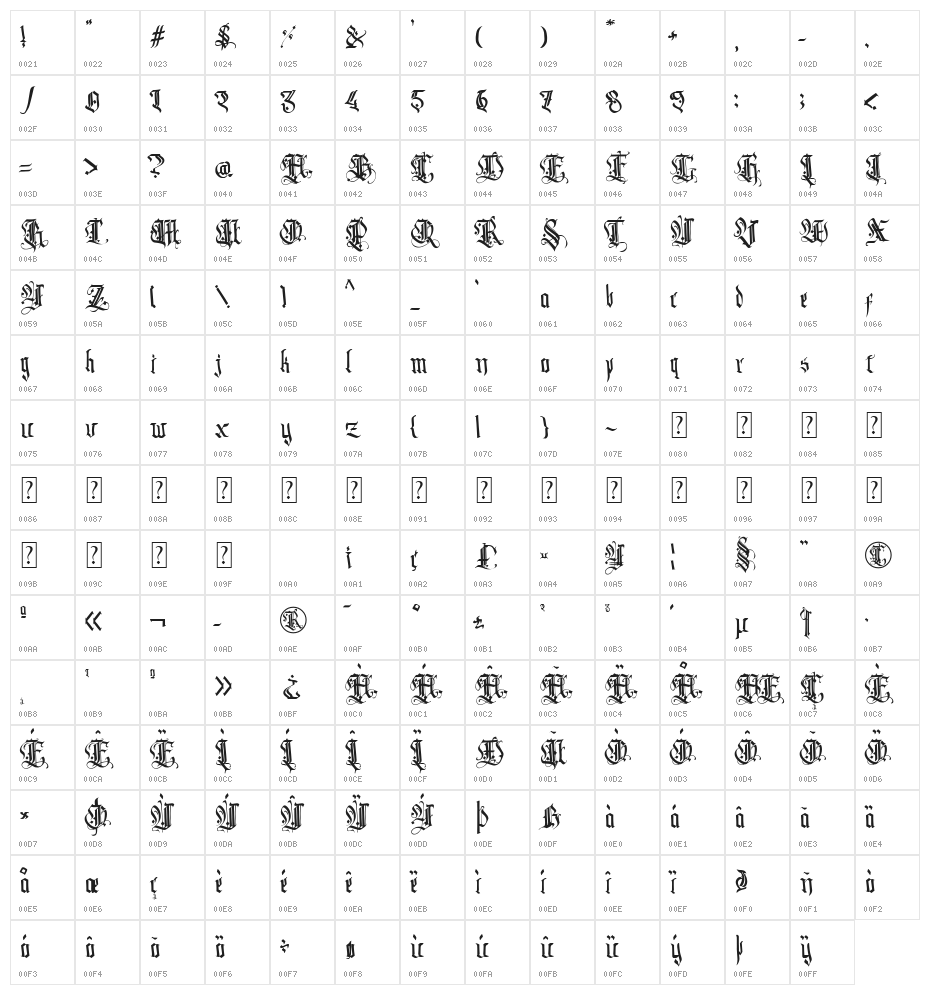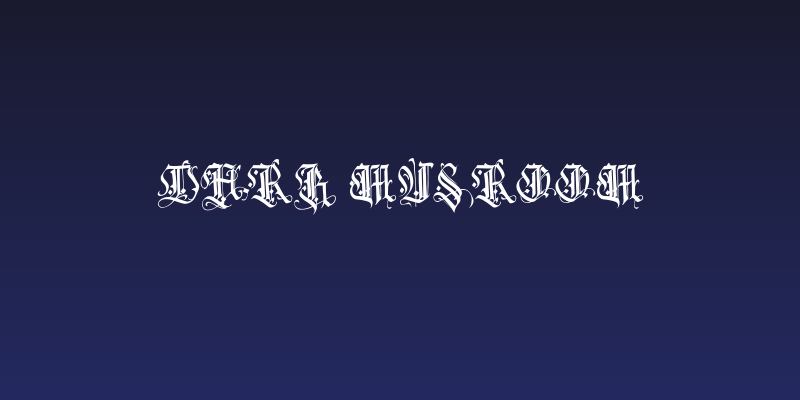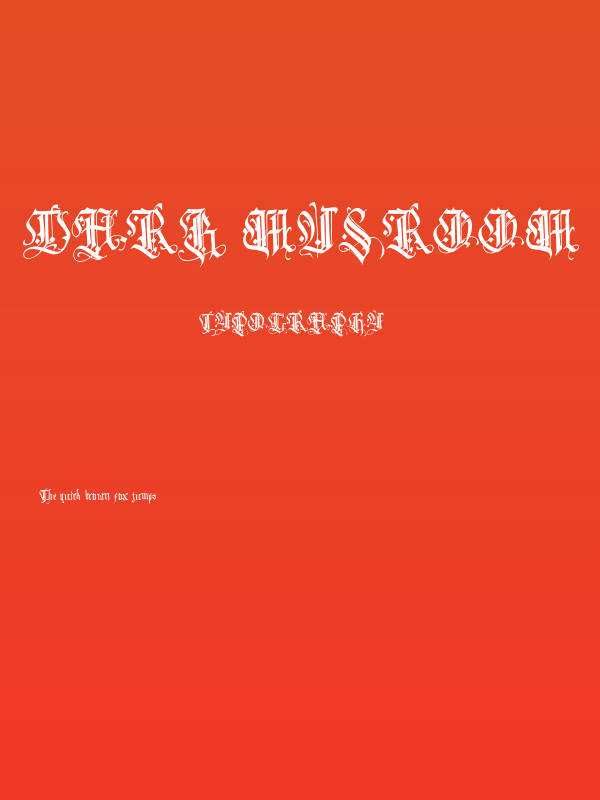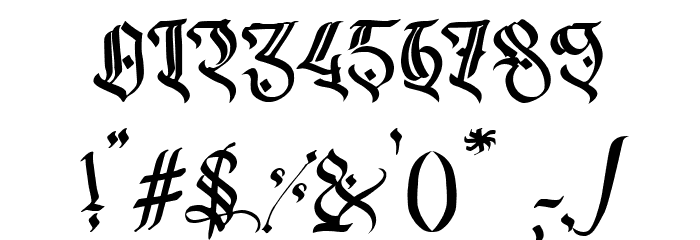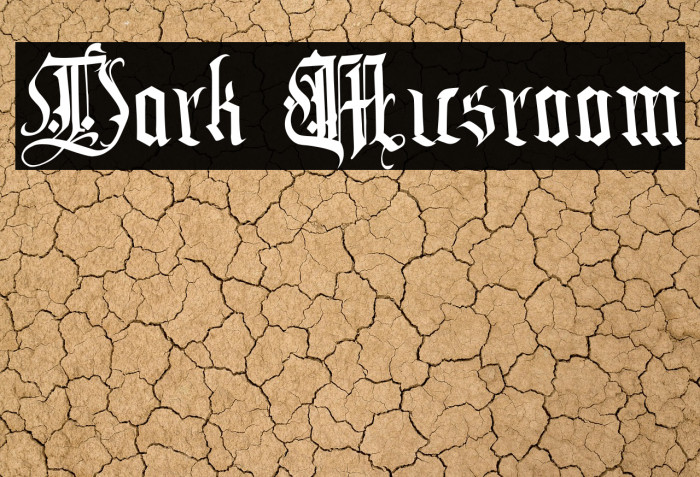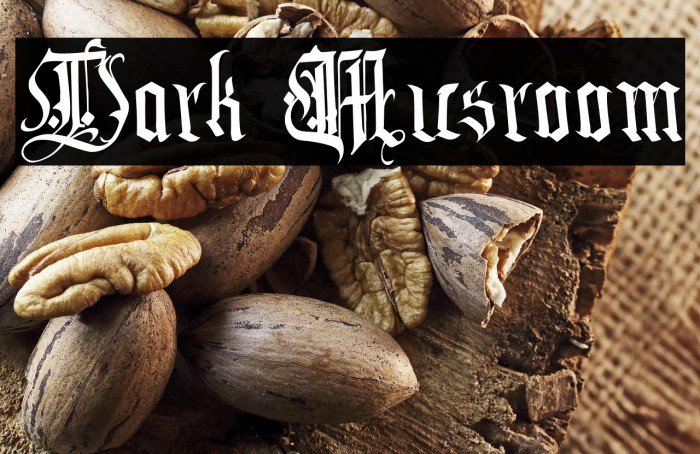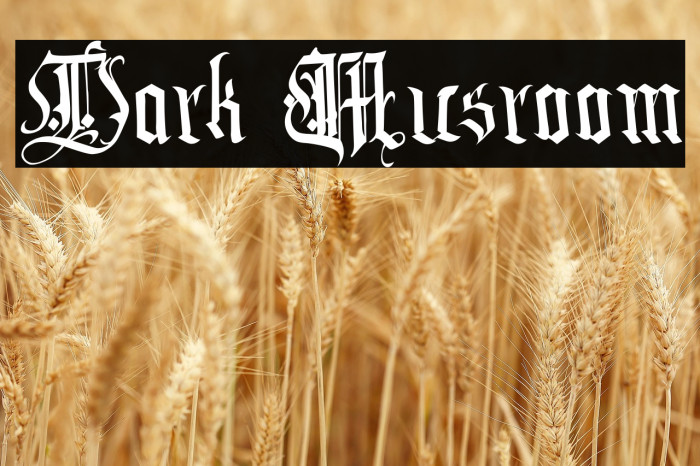
Dark Musroom Font
✎ Gothic
| Kategorien | Gothic |
| Gesamtstil | Vintage |
| Anwendungsfall | Logos, Headlines, Decorative text |
| Vorgeschlagene Projekte | Ideal for historical-themed designs, gothic art projects, invitations, and decorative signage. |